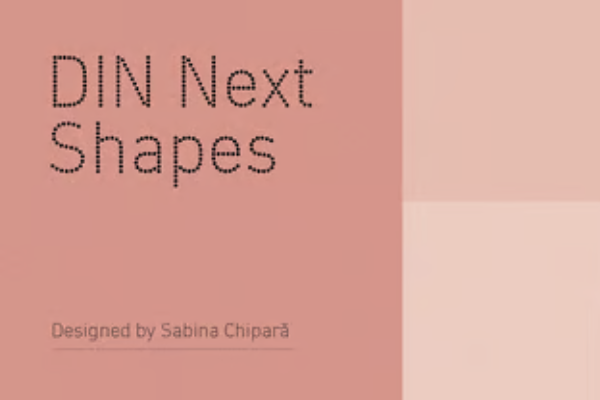
DIN® Next Shapes Flakes
DIN Next Shapes 采用了原始德国工业经典字体的骨架,并用圆点、心形、雪花和星星进行重新装饰,使其更平易近人和异想天开,同时它也保持了字形的易读性和清晰度。它可以与 DIN Next 字体协调配合,适合应用于更具表现力的设计与趣味性环境中,特别适合品牌推广。DIN Next Shapes 具有 OpenType 功能,支持泛欧语言,包括希腊语和西里尔语。